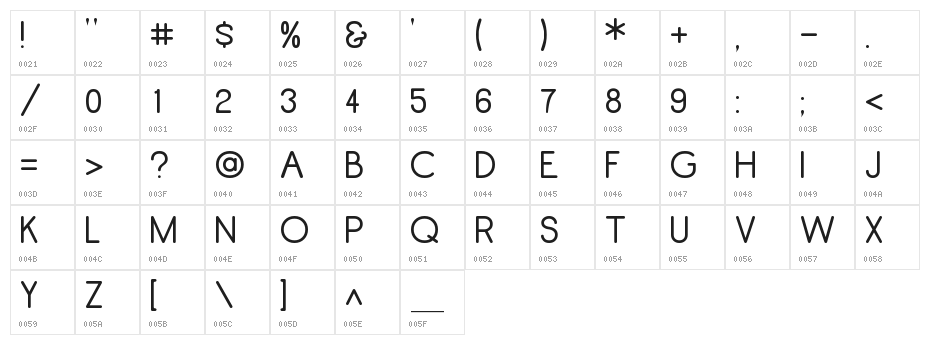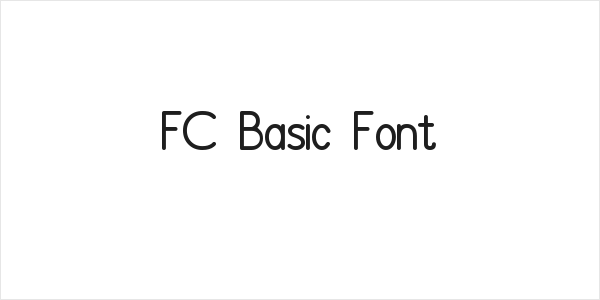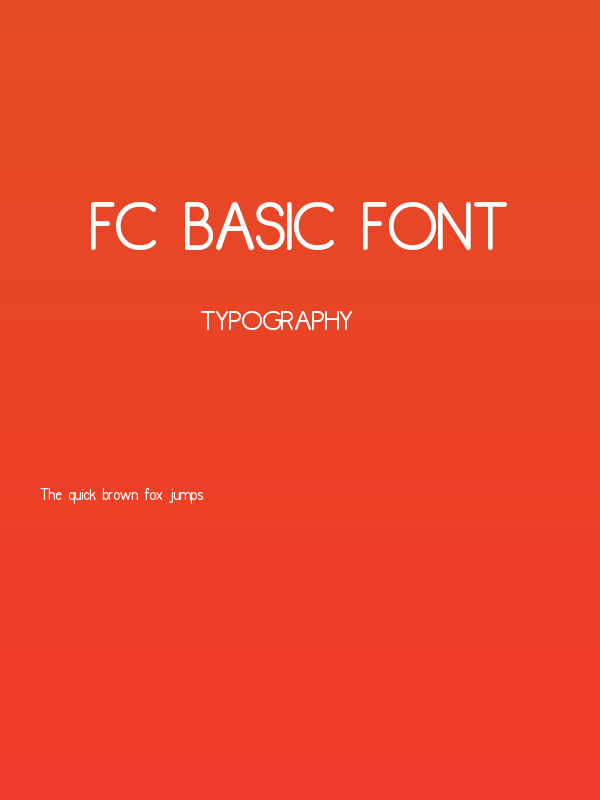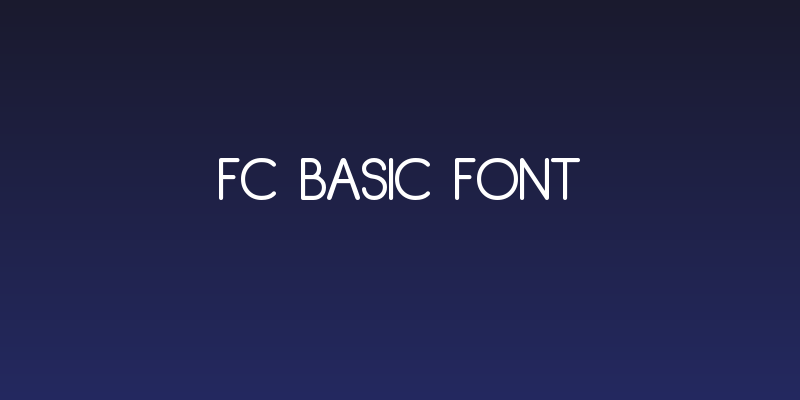
FC Basic Font Font
✎ Sans Serif
| Область применения | Headlines, Body text, Logos |
| Рекомендуемые проекты | Ideal for branding, user interfaces, signage, and educational materials due to its clarity and modern appeal. |